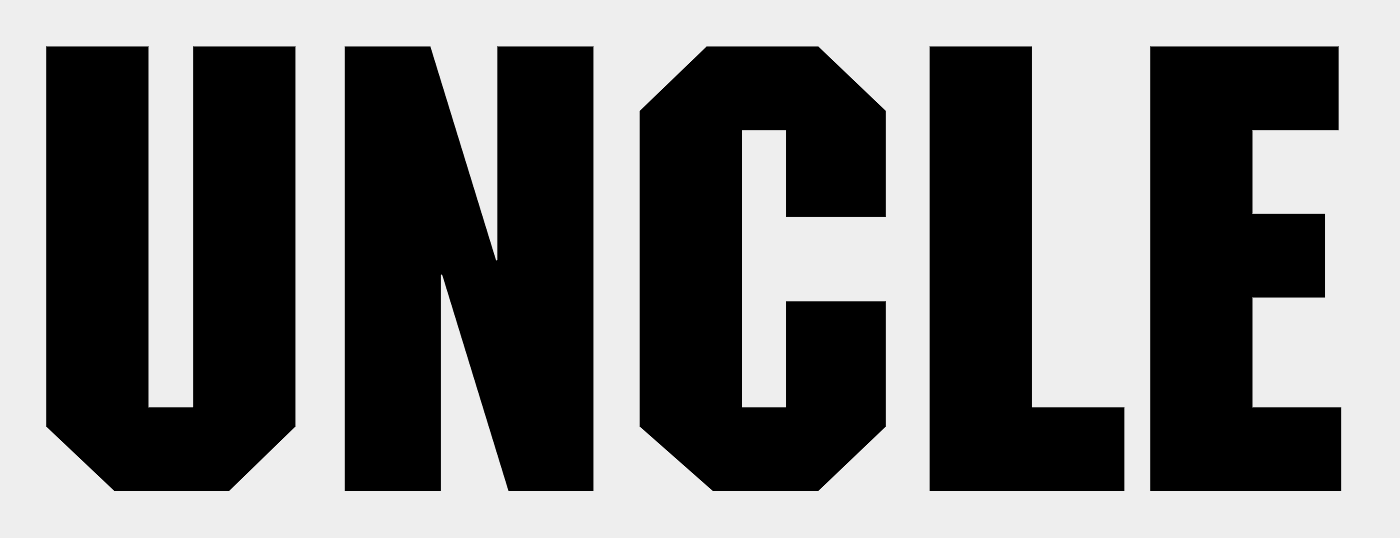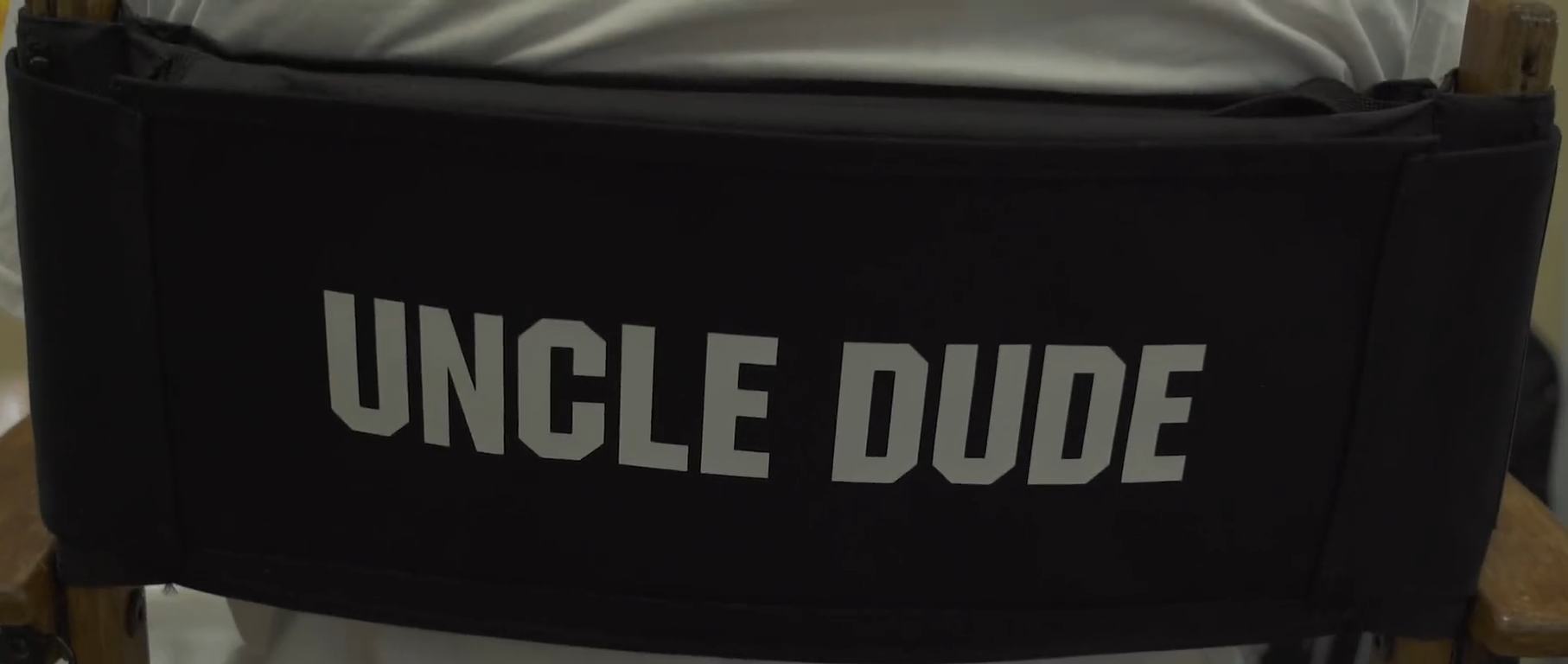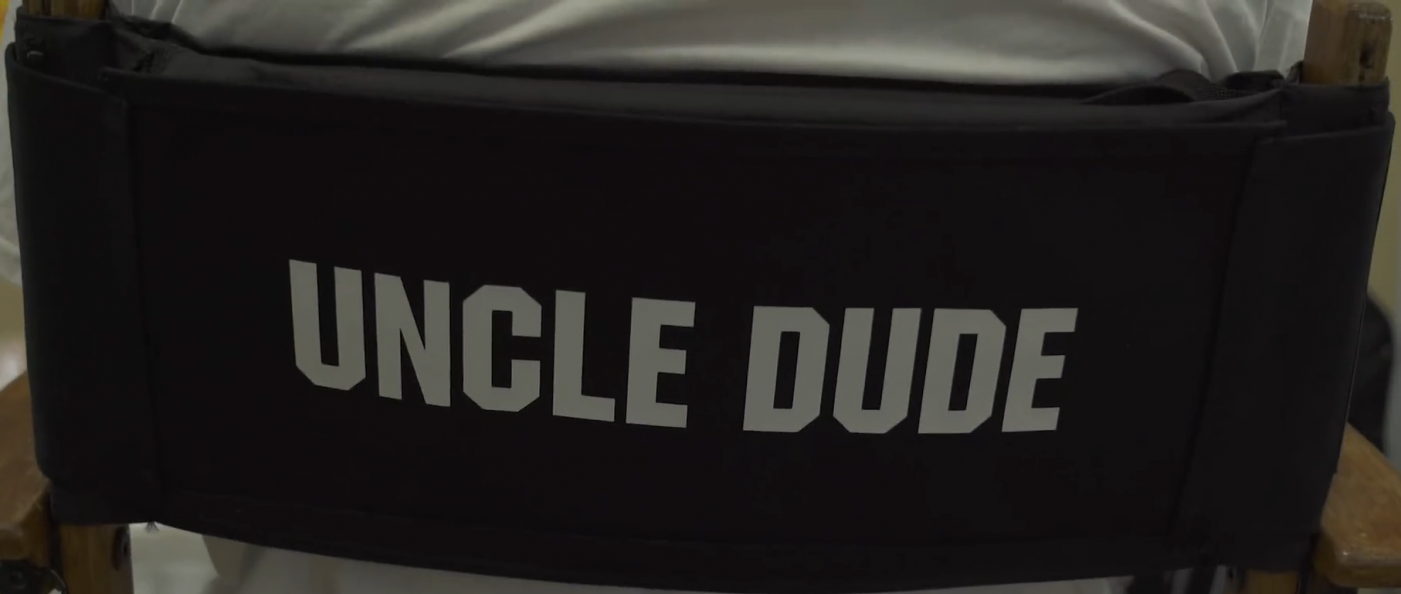
Welche Schrift wurde auf dem Screenshot, welches einem Video von "Dude Perfect" entnommen wurde, verwendet?
ich suche die Schrift auf dem angehängten Screenshot. Ich habe bereits einige optimierte Versionen des genannten Screenshots durch mehrere Font-Tools laufen lassen, allerdings wurde mir keine auch nur ansatzweise richtige Schrift angezeigt. Der Screenshot wurde einem Video des YouTube Kanals Dude Perfect entnommen. Weitere Informationen zur Schrift liegen mir nicht vor. Über Hilfe würde ich mich sehr freuen!
das sieht für mich wie eine etwas breit gezogene ITC Machine aus.
Aber da fällt mir was ein ... Wirf auch mal ein Äuglein auf die SF Collegiate:
Hier findest Du ähnliche Schriften, das Stichwort lautet College, Highschool, Sports ...
Vielen Dank für die schnelle Antwort. Die Schrift ITC Machine kommt der auf dem Screenshot verwendeten Schrift schon ziemlich nahe, es ist allerdings nicht die gleiche, was man besonders am Buchstaben "N" sehen kann.
Ich habe alles im Bereich College, Highschool, Sports etc. durchsucht, allerdings bin ich nicht fündig geworden.
Kann man? Ich sehe keine offensichtlichen Unterschiede. Ich würde sogar behaupten, gerade das N bestätigt, dass es diese Schrift ist. Die anderen Buchstaben sind so geometrisch, dass sie theoretisch auch in anderen Schriften vorkommen könnten. Das besondere N mit der schmalen Schrägen ist jedoch sehr eigen.
Möglicherweise gibt es Probleme mit der geometrischen Abbildung auf dem Foto und der ggf. manuellen Verbreiterung. Das N mit seinem sehr schmalen schrägen Strich ist ziemlich markant und in kaum einer anderen dieser Schriften zu finden, wie Ralf schon angemerkt hat. Ich bin noch mal meine Dokumentation durchgerannt und es waren wirklich fast keine Schriften mit einem so schmalen Schrägstrich dabei.
Diese Art von Lettern ist sehr beliebt für Sporthemden von Collegemanschaften. Aber das ist nicht der einzige Verwendungszweck.
Man sieht beim folgenden Link recht schön den Zusammenhang mit den Sportbeschriftungen und auch dass diese Lettern sehr leicht nachzuschneiden sind.
Hinweis: Große Buchstaben preiswert herzustellen geht damit auch, siehe den Schirftzug HOLLYWOOD. Die ITC Machine wurde nach den Buchstaben dieses Schriftzuges geschaffen. Schon daher wäre es nur zu logisch diese auf Regiestühlen zu verwenden.
Typefaces: The Hollywood Sign